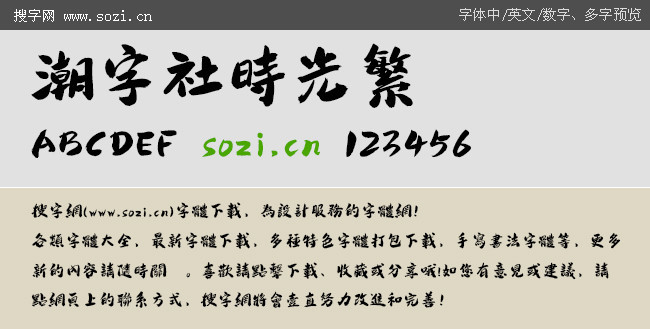
潮字社時光繁
搜字網(wǎng)提供一款潮字社時光繁中文字體下載,潮字社時光體剛毅中又平添柔和,整體方正飽滿,視覺沖擊力強,力量感突出,節(jié)奏分明,充滿藝術(shù)張力,適用于書籍封面設(shè)計、報刊標頭設(shè)計,包裝設(shè)計,海報設(shè)計等廣告應(yīng)用。(此款為個人非商用版,如需商用請聯(lián)系銳字工房購買)